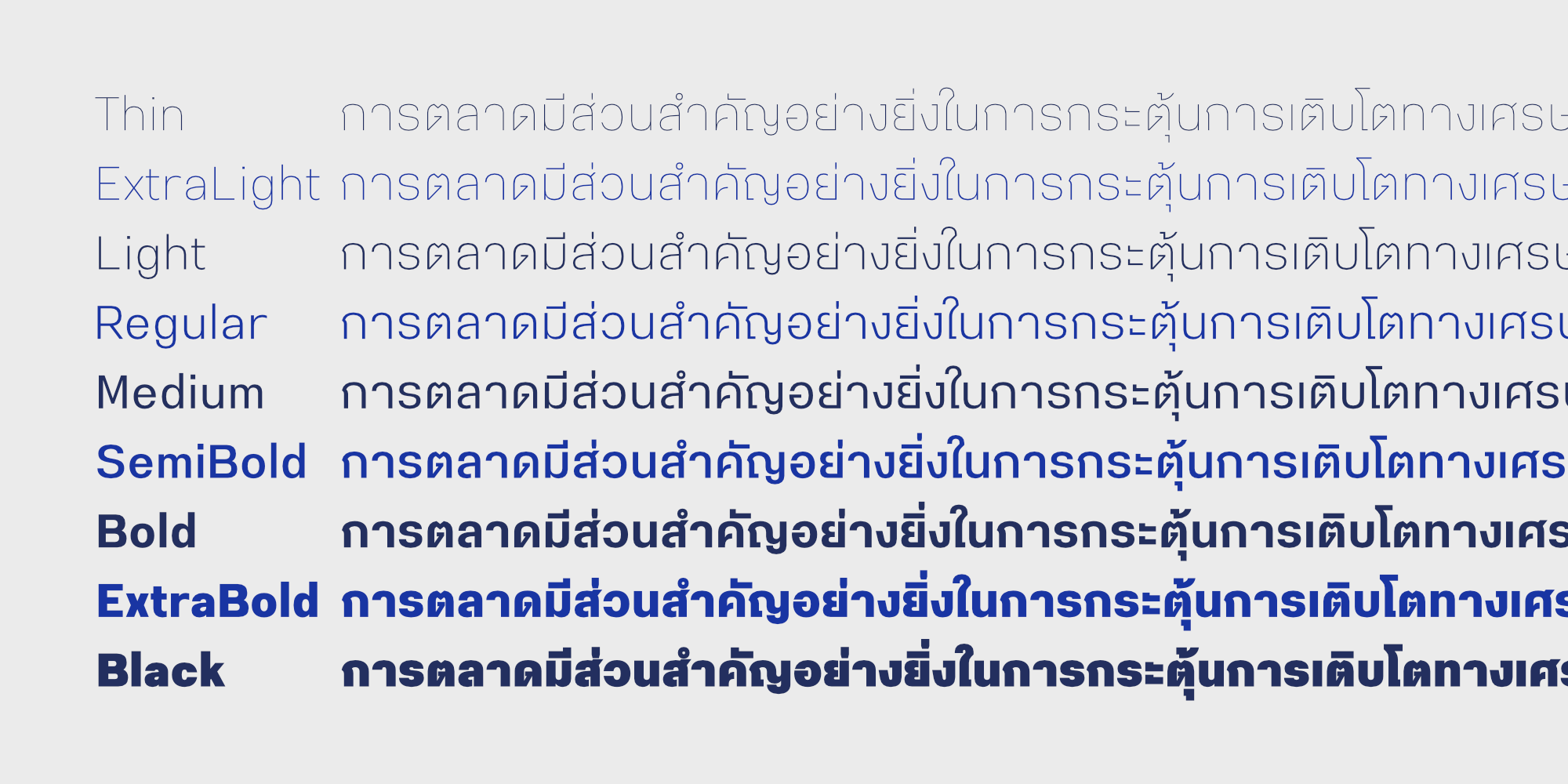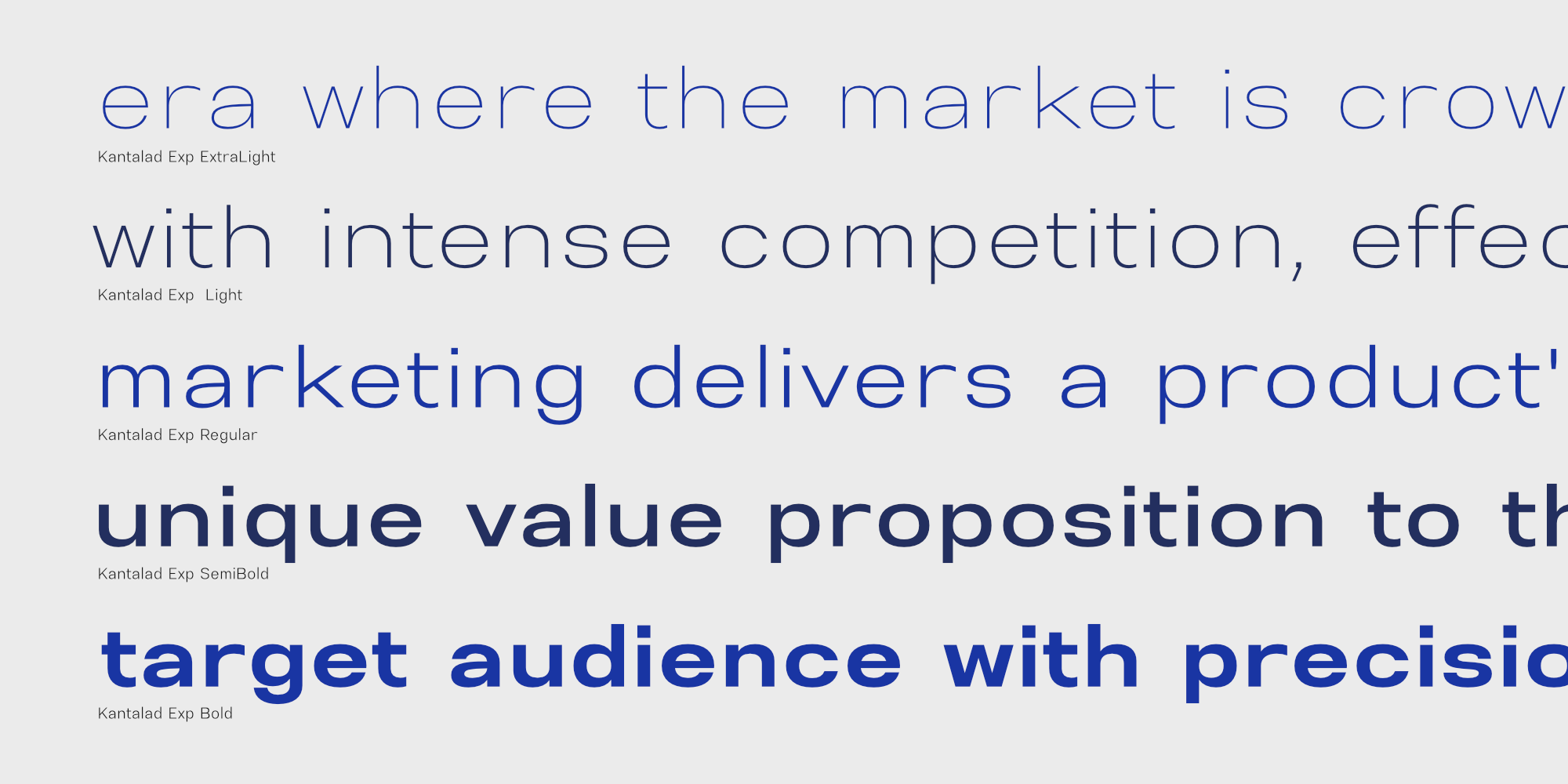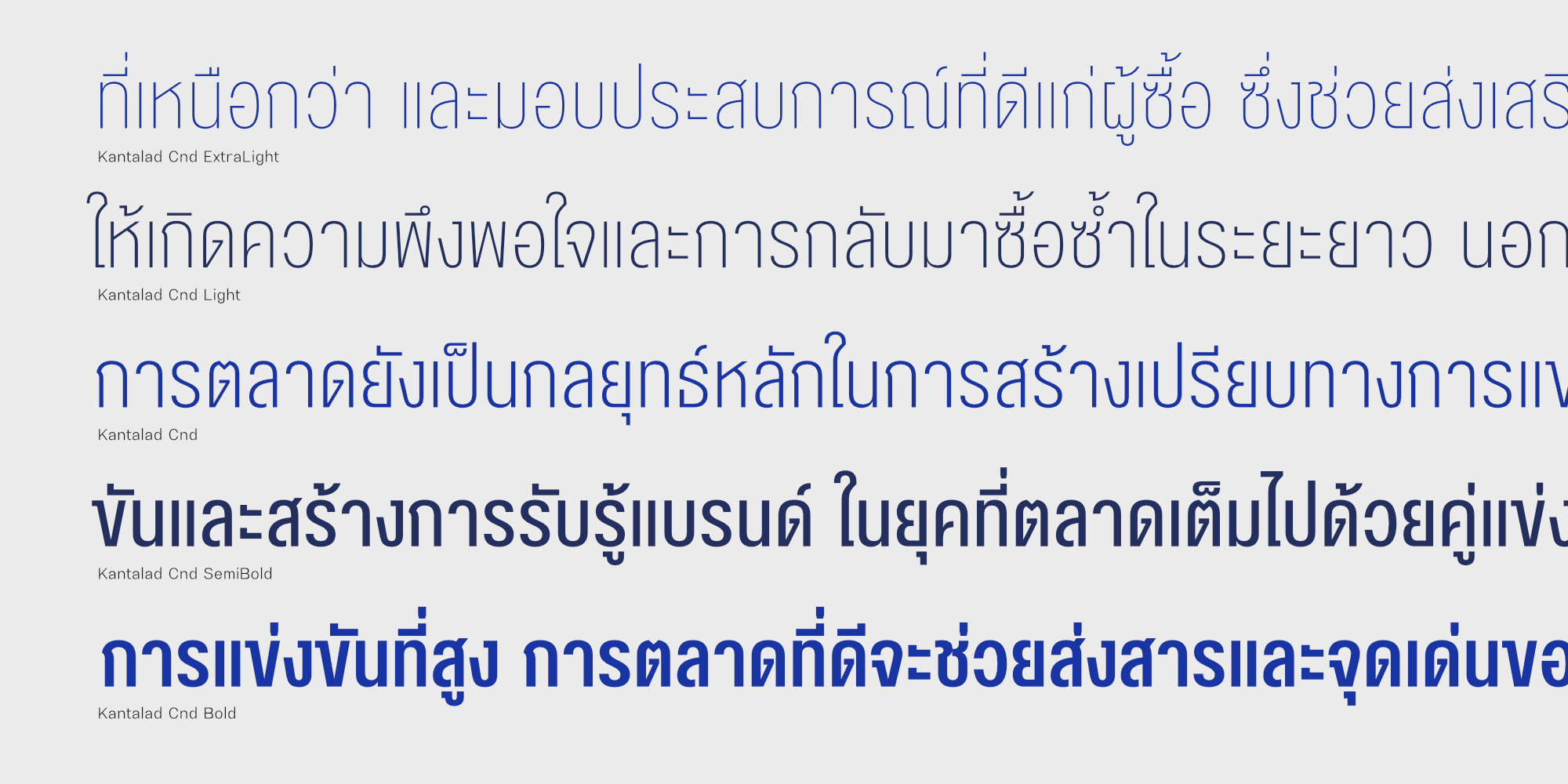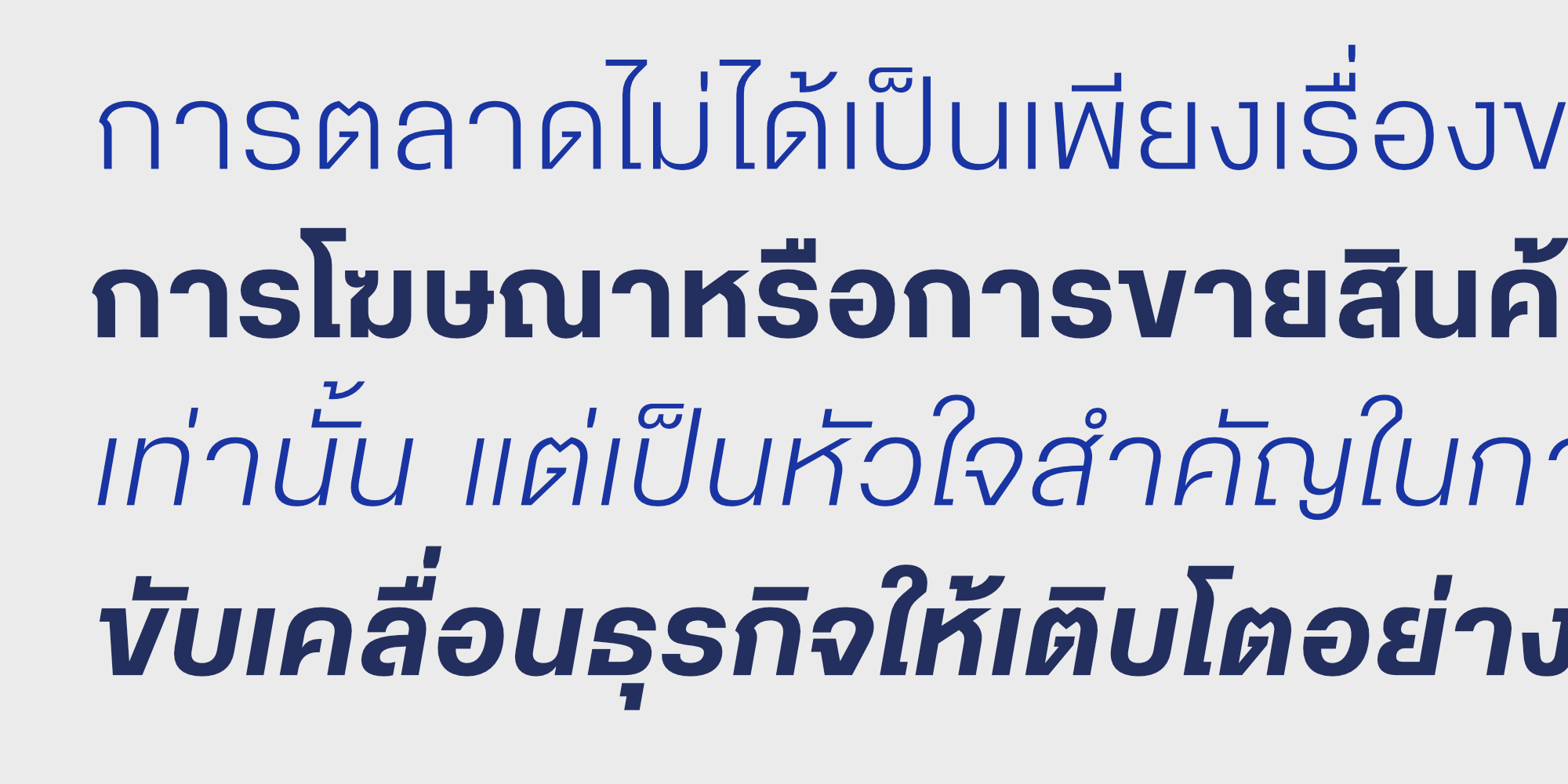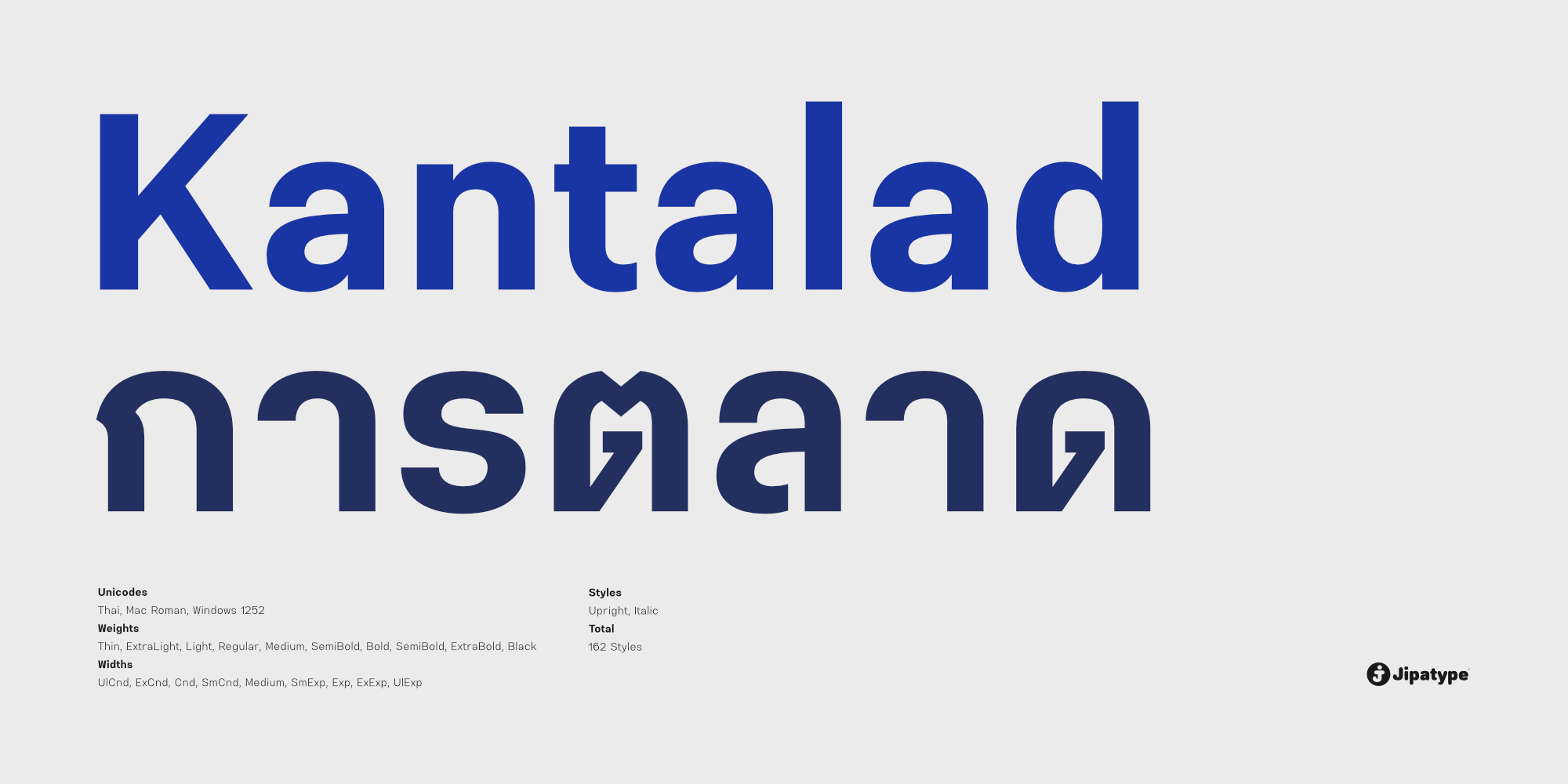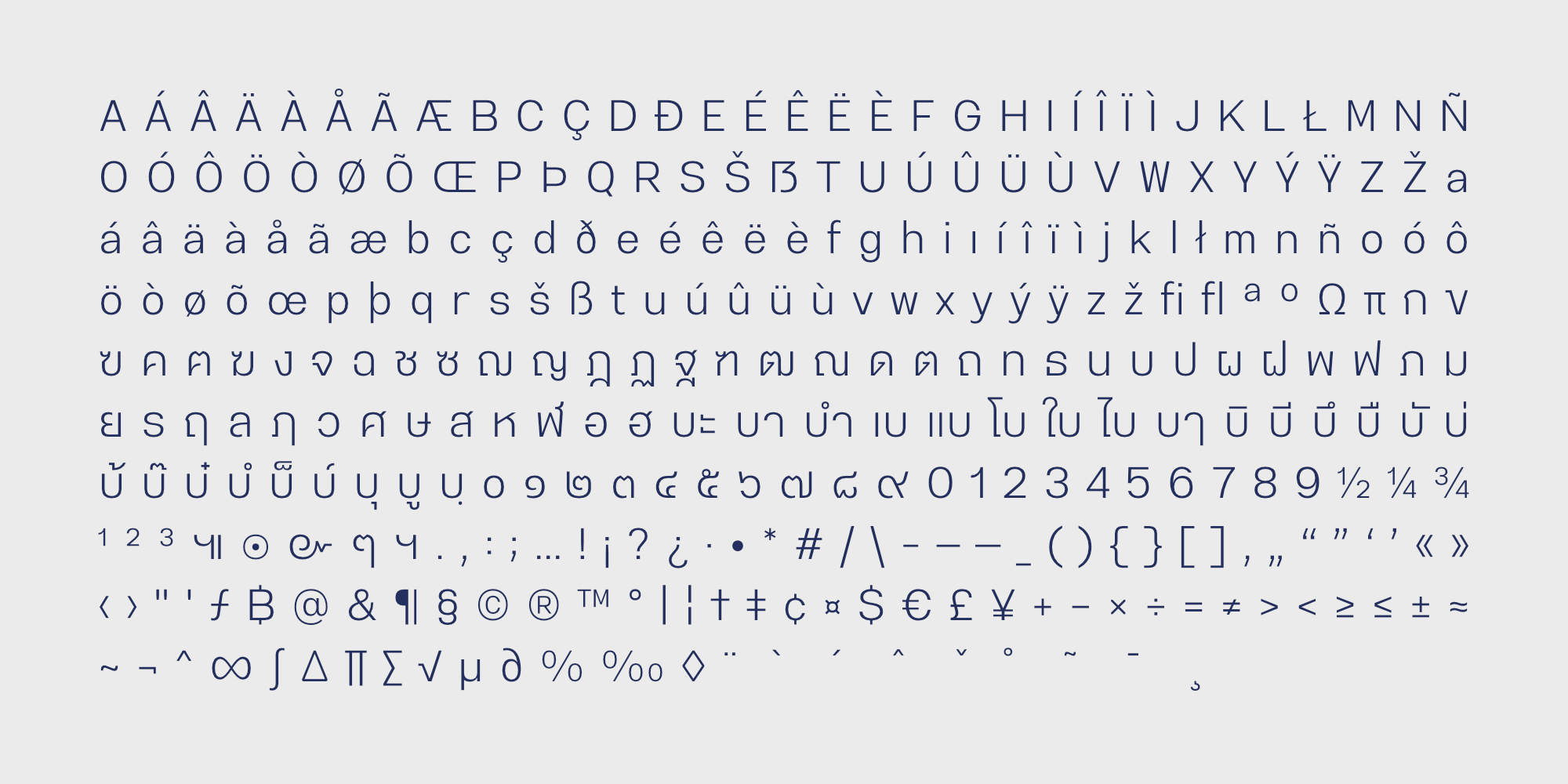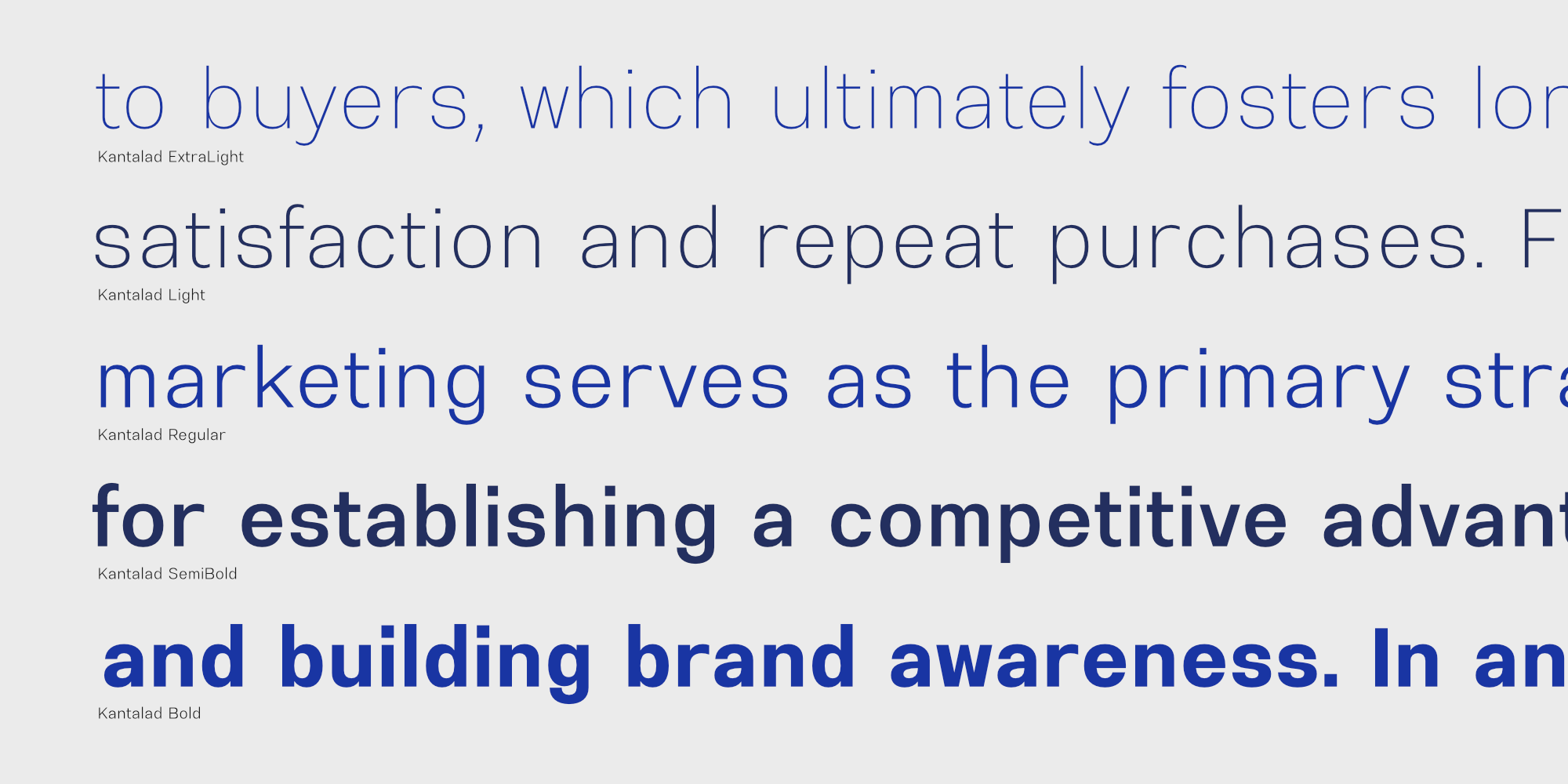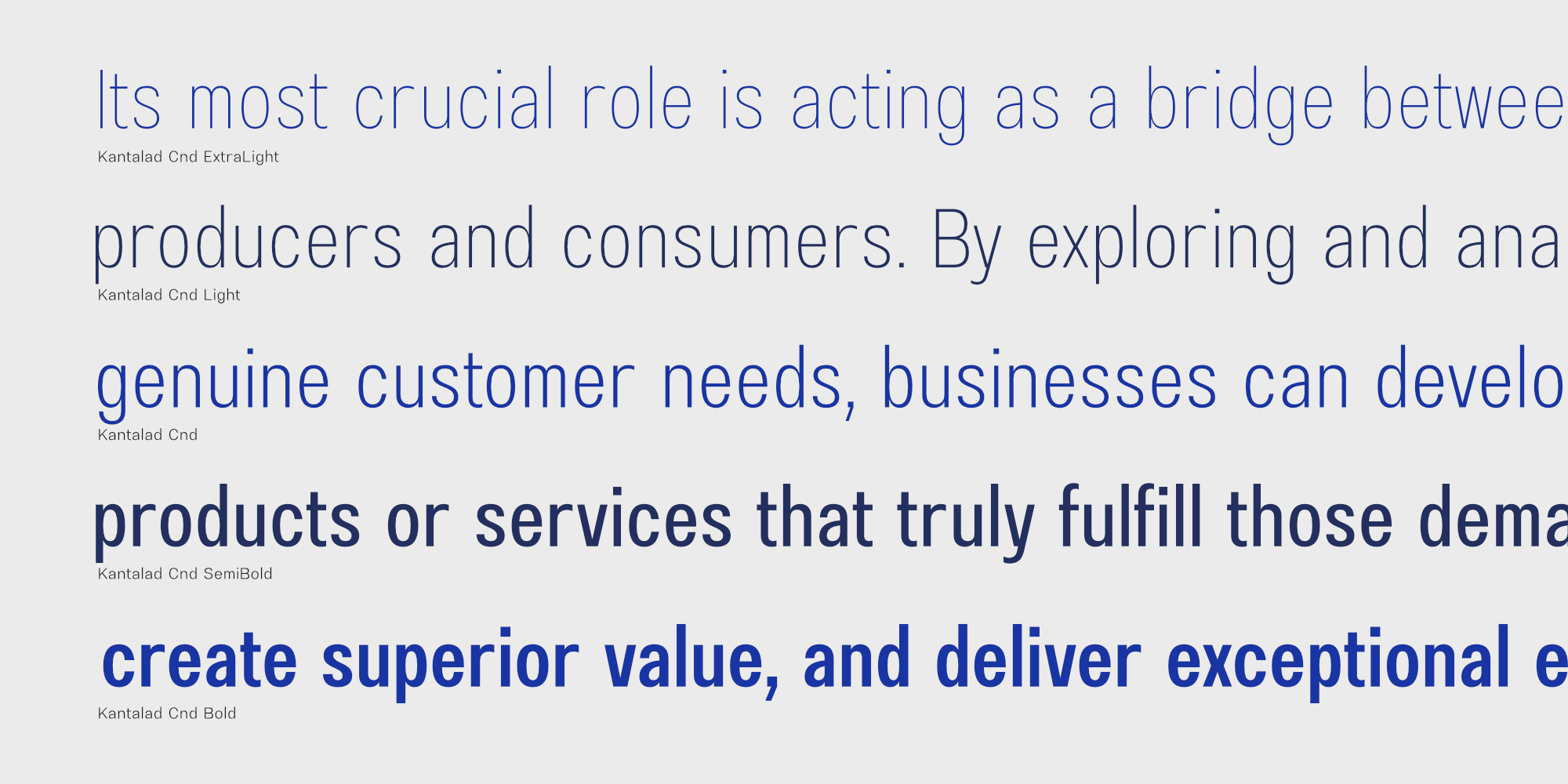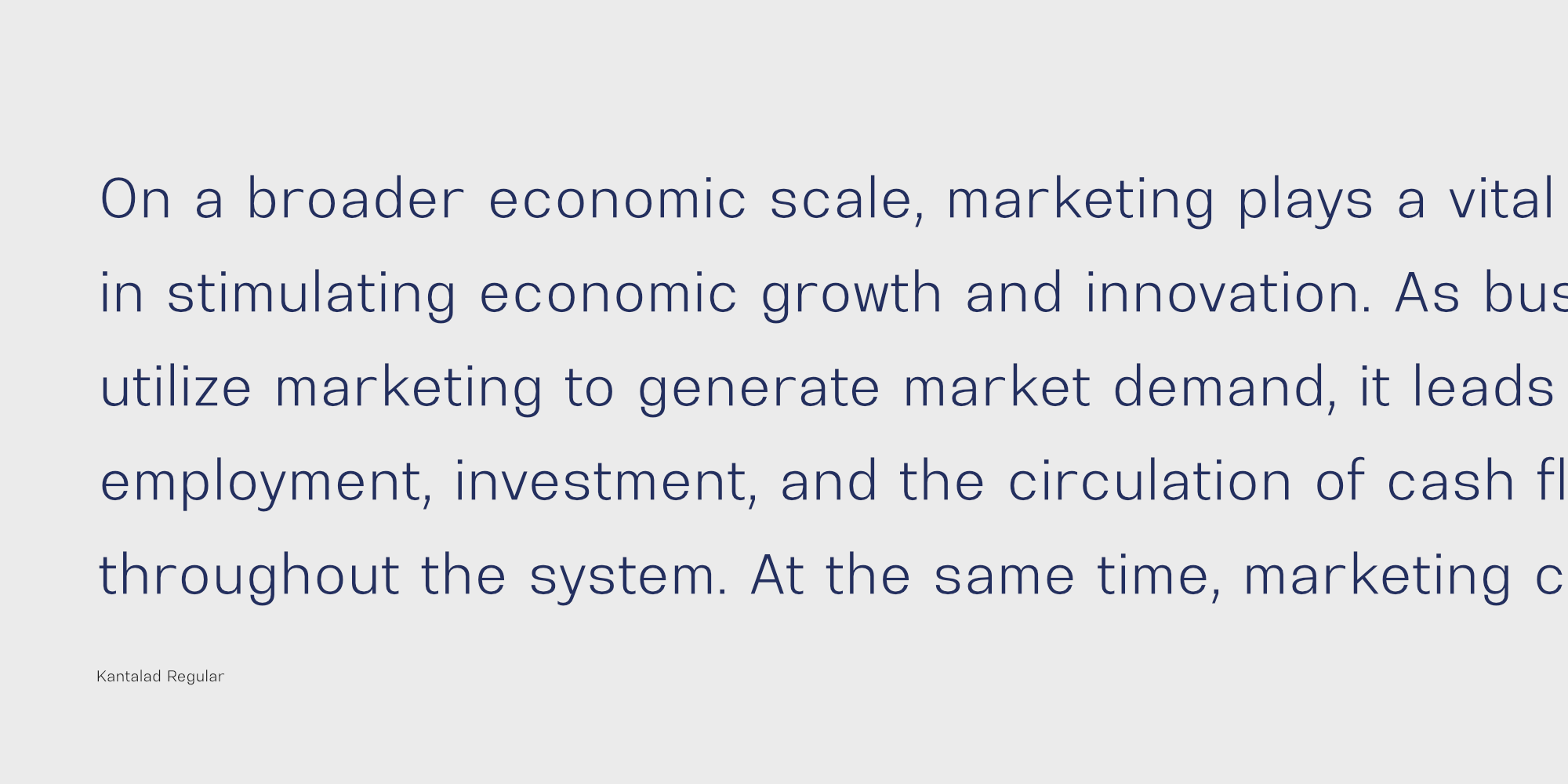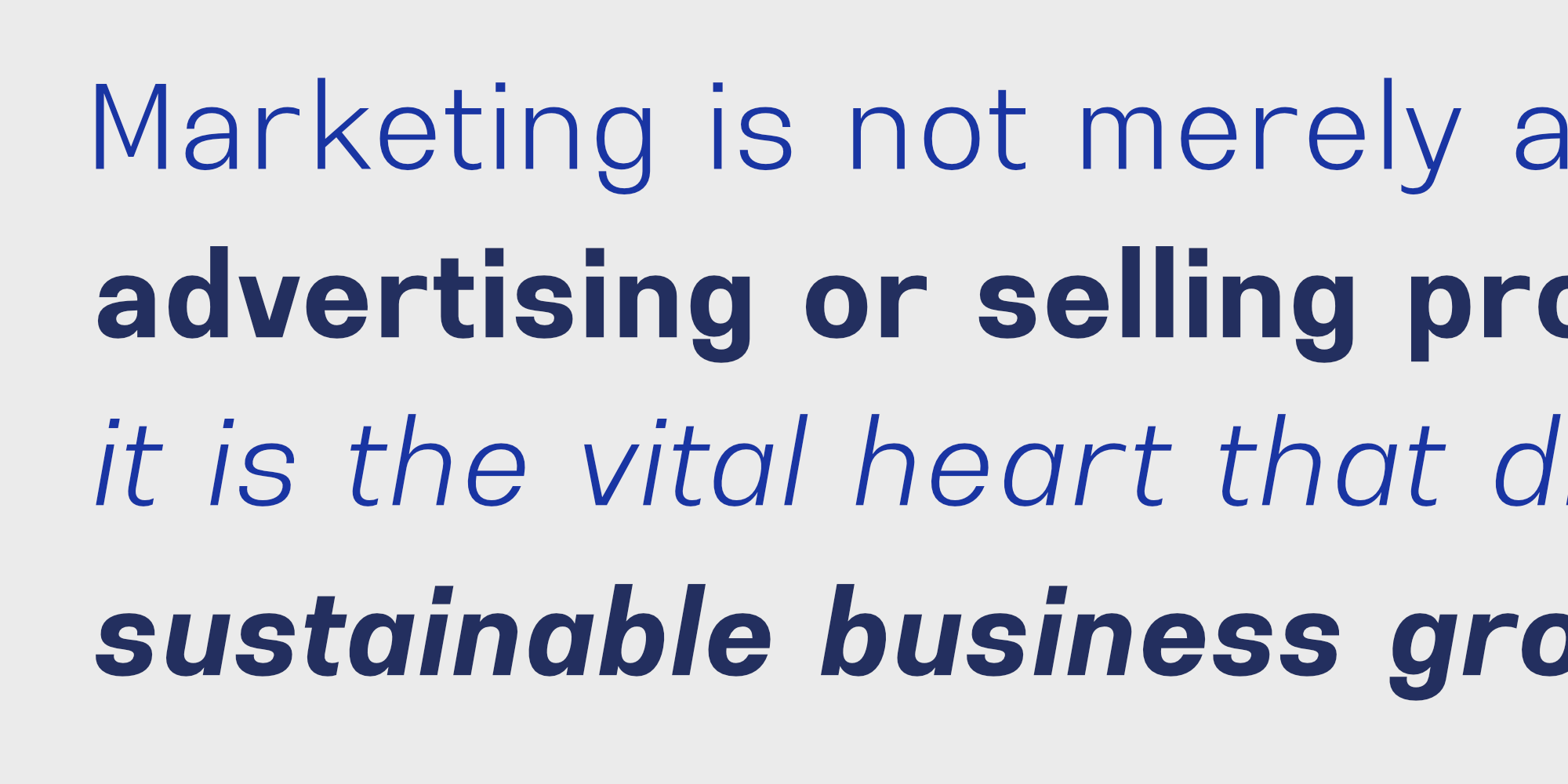
การตลาด | Kantalad
Kantalad เป็นแบบอักษรแซนเซอริฟที่แสนเรียบง่าย ได้รับแรงบันดาลใจจากแบบอักษรยอดนิยมที่แบรนด์สินค้าชั้นนำในไทยชอบหยิบยกมาใช้กันบ่อยครั้ง จิปาไทป์จับอารมณ์ความรู้สึกนั้นมาวาดใหม่อีกครั้งตั้งแต่เริ่มต้น มีความกว้างตั้งแต่ UlCnd  (Ultra Condensed) ถึง UlExp (Ultra Expanded) รวม 9 ความกว้าง โดยอัตราส่วนความกว้างกำหนดให้ความกว้างปกติคือ 100 เปอร์เซ็นต์ UlCnd คือ 50 เปอร์เซ็นต์ และ UlExp คือ 150 เปอร์เซ็นต์ของความกว้างปกติ มีน้ำหนักตั้งแต่ Thin ถึง Black รวม 9 น้ำหนัก และตัวเอียงของแต่ละน้ำหนัก รวมทั้งสิ้นมี 162 สไตล์